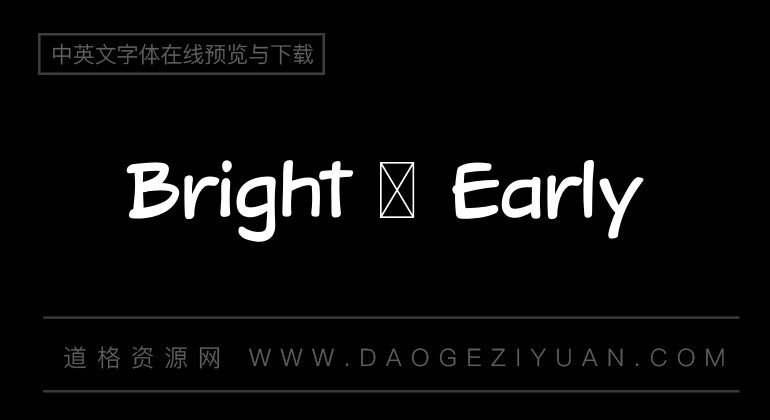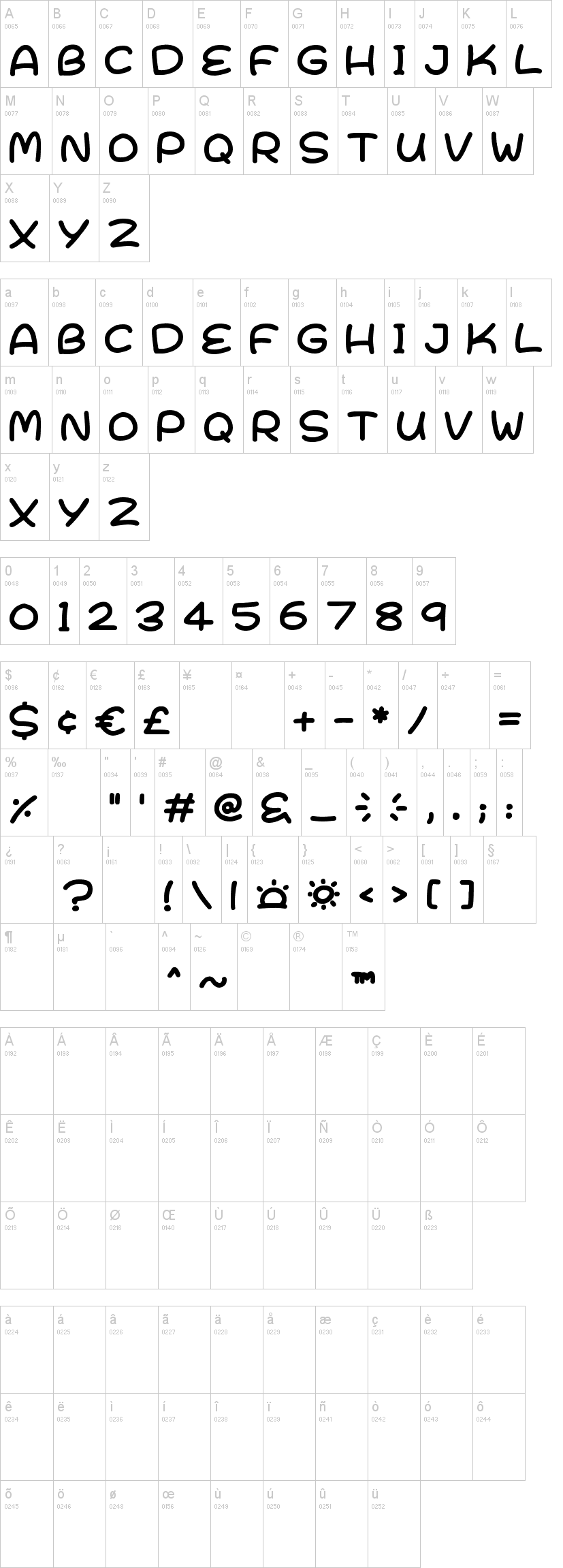
Bright & Early
Bright & Early 是一款由 type designer David Jonathan Ross 创作的儿童字体,它具有清晰、可读性强的特点,让孩子们更容易理解。字体有两种风格:一种是拉丁文风格,另一种是斯拉夫风格。它们都具有清晰、可读性强的特点,让孩子们更容易理解。Bright & Early 字体还具有良好的视觉效果,可以让孩子们更容易地阅读和理解文字,从而提高他们的学习能力。
Bright & Early是一款非常不错的手写艺术字体,具有很好的视觉感,适合于文化类的宣传设计、商业类品牌的广告和产品包装设计以及个性化文字排版等较多场景。